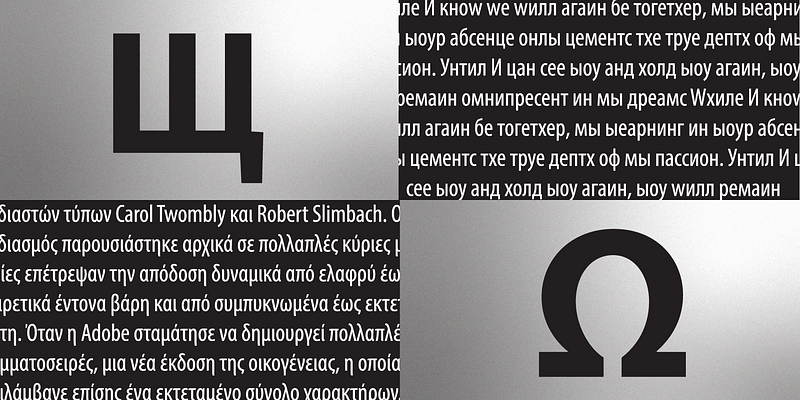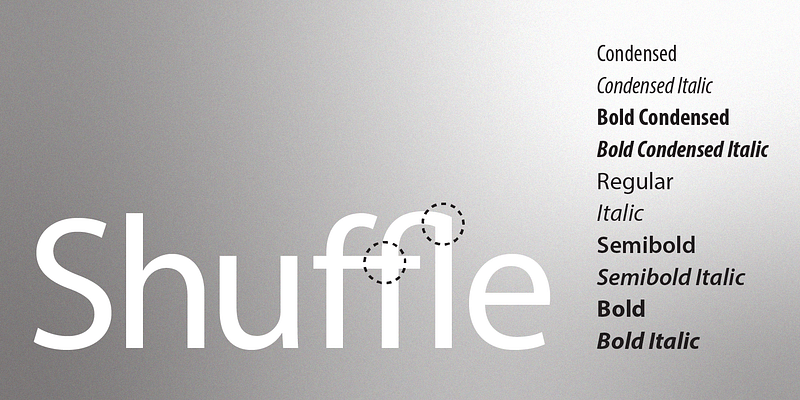
Myriad, ein Design von Adobe Originals, das erstmals 1992 veröffentlicht wurde, ist sowohl für die Text- als auch für die Displaygestaltung beliebt. Als OpenType-Version erweitert Myriad Pro diese serifenlose Schriftfamilie um griechische und kyrillische Glyphen, fügt Mediävalziffern hinzu und verbessert die Unterstützung für lateinische Sprachen. Die gesamte Myriad Pro-Familie umfasst Condensed-, Normal- und Extended-Breiten in einer ganzen Reihe von Strichstärken. Myriad wurde von Robert Slimbach & Carol Twombly in Zusammenarbeit mit Fred Brady & Christopher Slye entworfen und zeichnet sich durch Wärme und Lesbarkeit aus, die aus der humanistischen Behandlung von Buchstabenproportionen und Designdetails resultieren. Die klaren, offenen Formen der Myriad Pro, die präzise Passung der Buchstaben und die umfangreichen Kerning-Paare machen diese einheitliche Familie von Roman und Italic zu einer ausgezeichneten Wahl für Texttypografie, die angenehm zu lesen ist, während die große Vielfalt an Strichstärken und -breiten der Familie eine großzügige kreative Palette selbst für die anspruchsvollste Display-Typografie bietet. Zum Patent angemeldetes Design.
Das Adobe Originals-Programm wurde 1989 als hauseigene Foundry bei Adobe gegründet, um Originalschriften von beispielhafter Designqualität, technischer Treue und ästhetischer Langlebigkeit zu entwickeln.
Heute besteht die Aufgabe des Type-Teams darin, anspruchsvolle und sogar experimentelle Schriften zu entwickeln, die die Möglichkeiten von Design und Technologie ausloten. Die Schriftarten, die als Adobe Originals veröffentlicht werden, sind das Ergebnis jahrelanger Arbeit und Studien und gelten als Industriestandard für den Ehrgeiz und die Qualität ihrer Entwicklung.